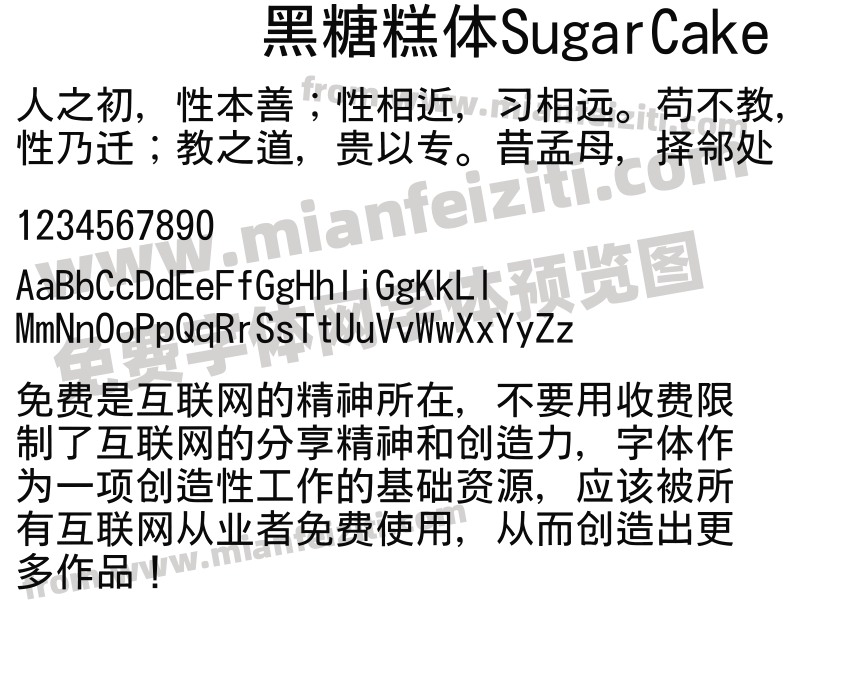
黑糖糕体是@Luke036基于汤圆体转换而成黑体字型。
“黑糖糕体”的特点是笔画流畅,而且与其他黑体字体相比,它的字间距相对较小,更加紧凑。该字体支持简体中文和繁体中文,同时还包括了一些特殊符号和日文假名。
由于其可爱的风格和易读性,该字体被广泛应用于各种设计领域,如网页设计、海报设计、印刷品设计等。同时,它也因为免费而受到很多设计爱好者的青睐。
本款“黑糖糕体SugarCake”是一款书写很新颖的字体,字体大方,适合各种设计作品使用!欢迎下载!